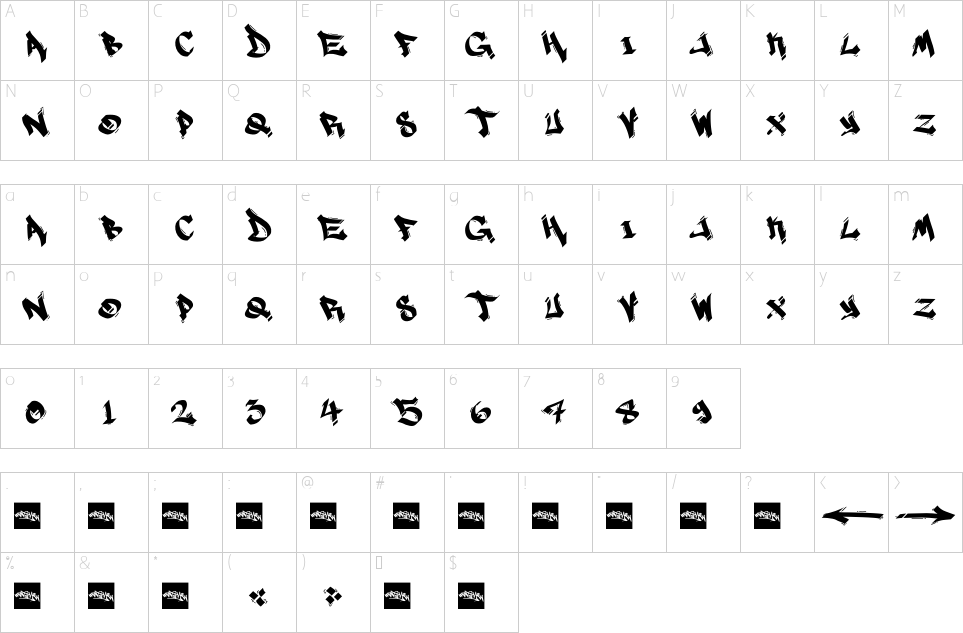
Aqui está uma descrição em português, envolvente e natural, para a página de download da fonte ‘Marsneveneksk Font’: Através da sua página de download, você tem a oportunidade de explorar a sofisticada Marsneveneksk Font. Desenhada pelo artista independente Marsnev, esta fonte abraça uma elegância única que se sobressai em qualquer aplicação. Com uma versão compatível para Windows e Mac, você pode experimentar a versão finalizada e perfeita desta criação artística. Marsneveneksk foi projetada para trazer um toque moderno e sofisticado ao seu design gráfico, seja para contratos formais ou criações digitais. Ao todo, mais de 500.000 downloads comprovam o seu valor e capacidade de se adaptar a diversos ambientes de design. Se você é um designer ou criativo que procura uma fonte de alta qualidade para dar um toque único à sua obra, a Marsneveneksk Font é uma excelente escolha.